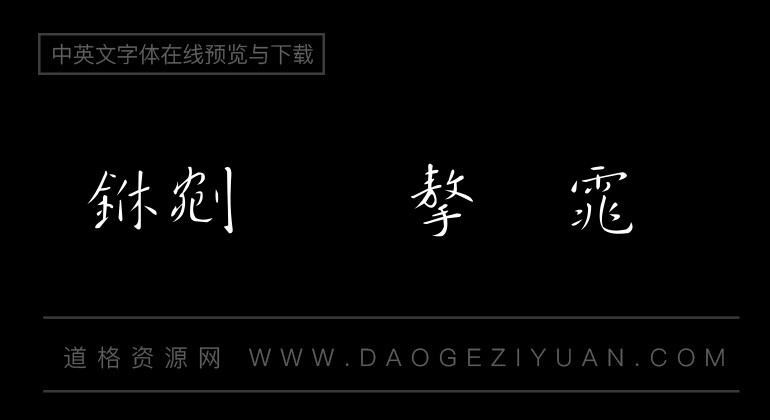
书法家行书体
书法家行书体是一种中国传统书法字体,它以宋体为基础,结合当时书法家的个人风格而形成。它具有细腻的线条,结构紧凑,曲线优美,字体清晰,笔画流畅,表现力强,节奏感强等特点。书法家行书体的字体具有深厚的文化底蕴,被广泛应用于书法、绘画、国画、篆刻等艺术领域,是中国书法的精华。
书法家行书体是一款非常不错的手写艺术字体,具有很好的视觉感,适合于文化类的宣传设计、商业类品牌的广告和产品包装设计以及个性化文字排版等较多场景。